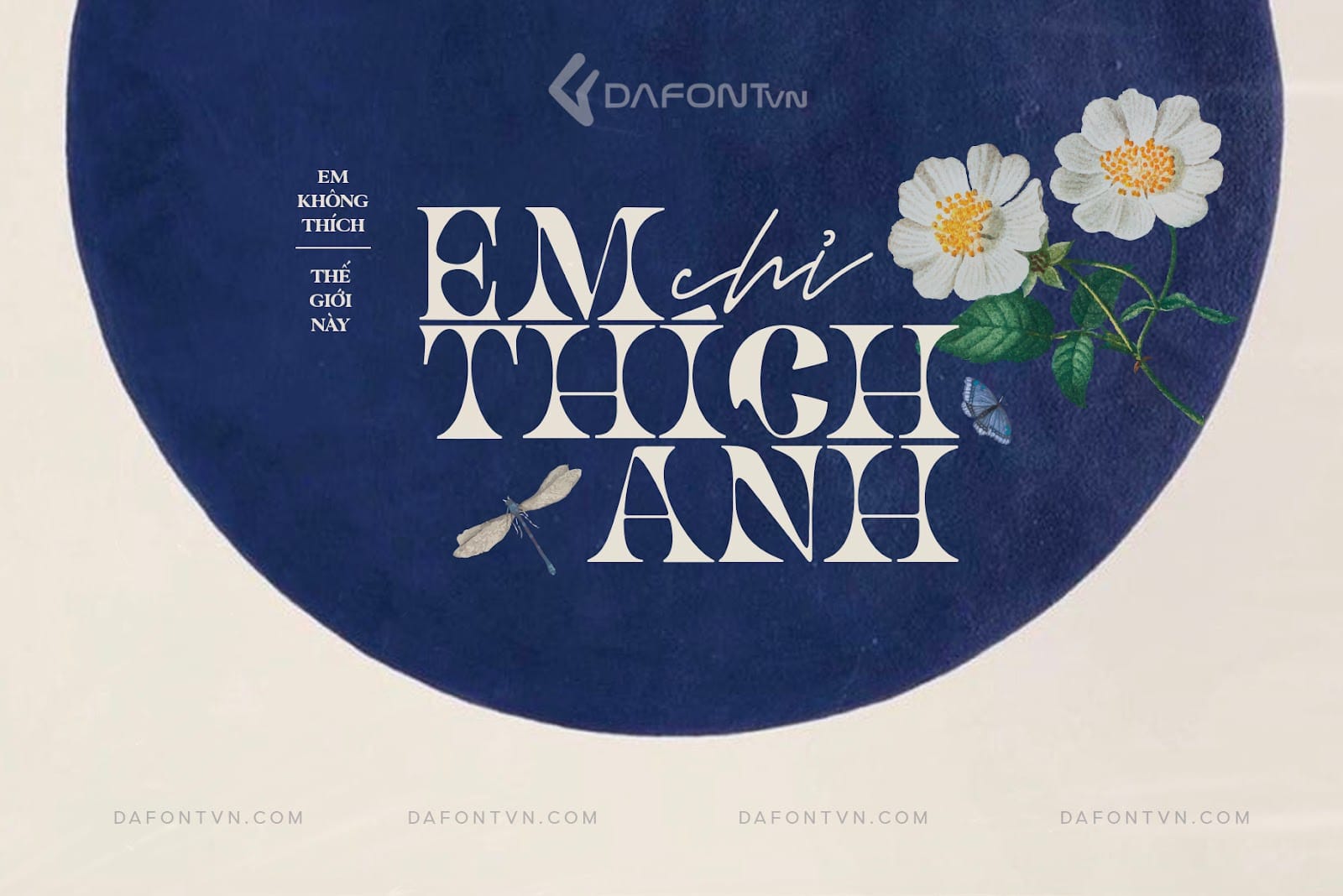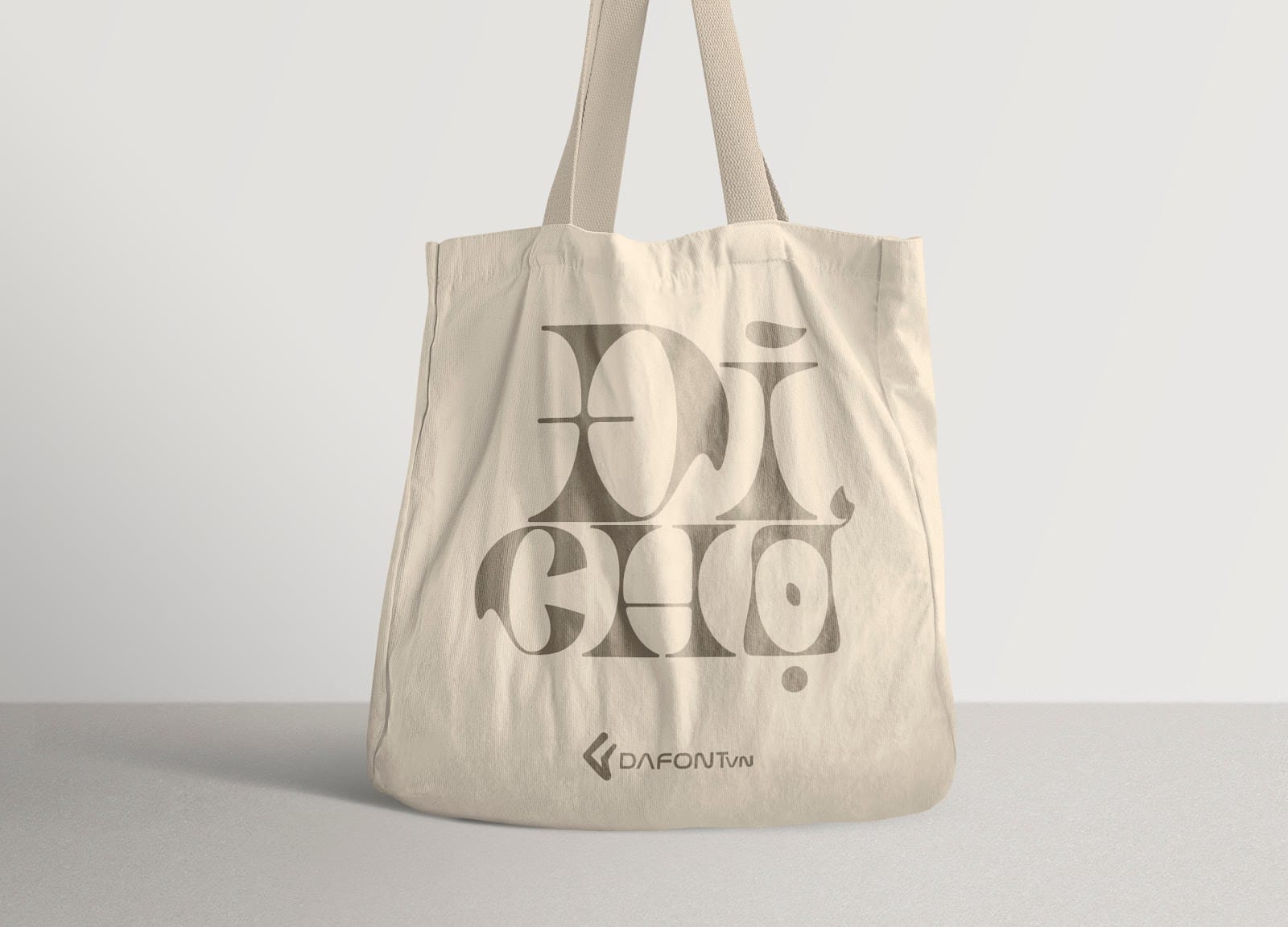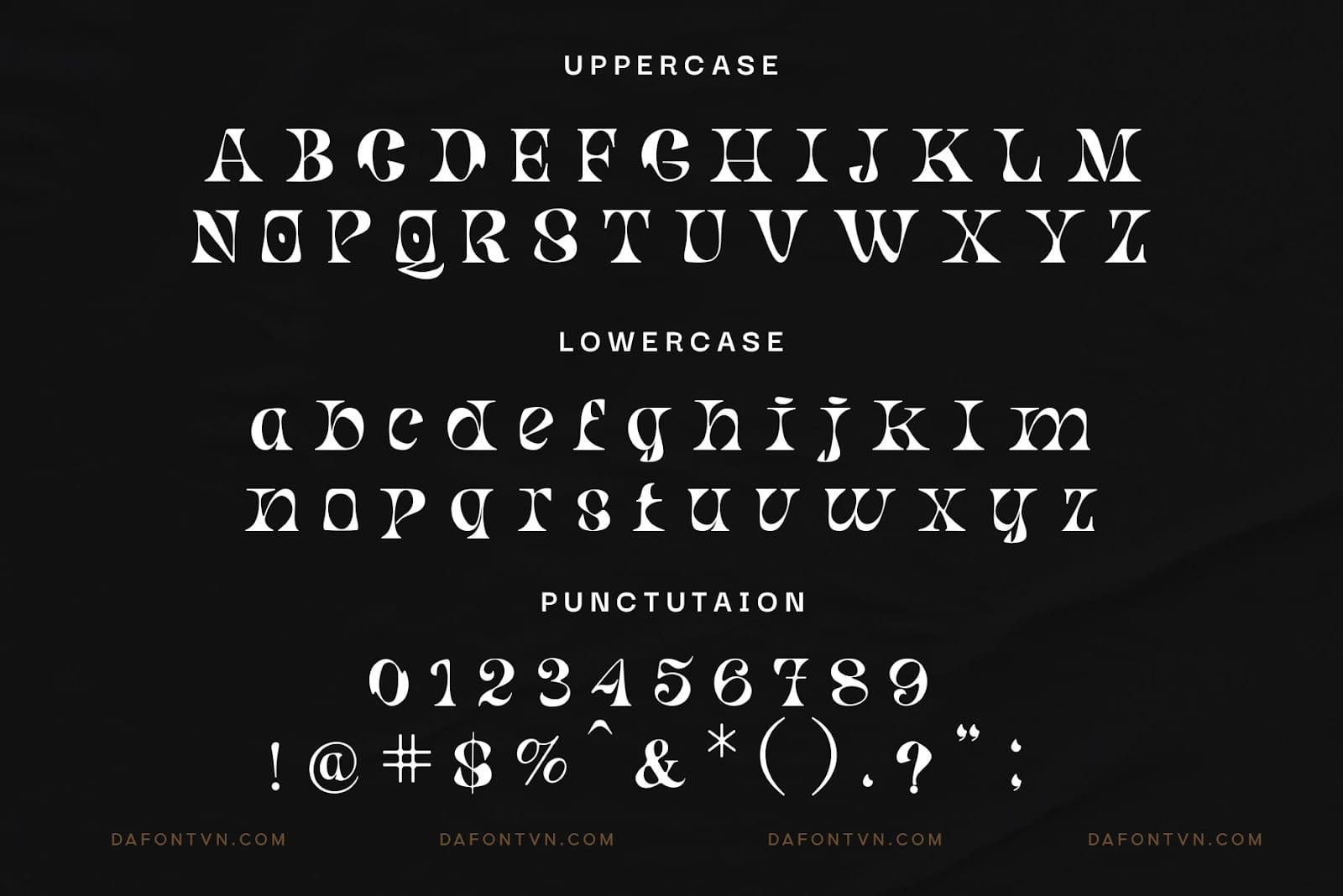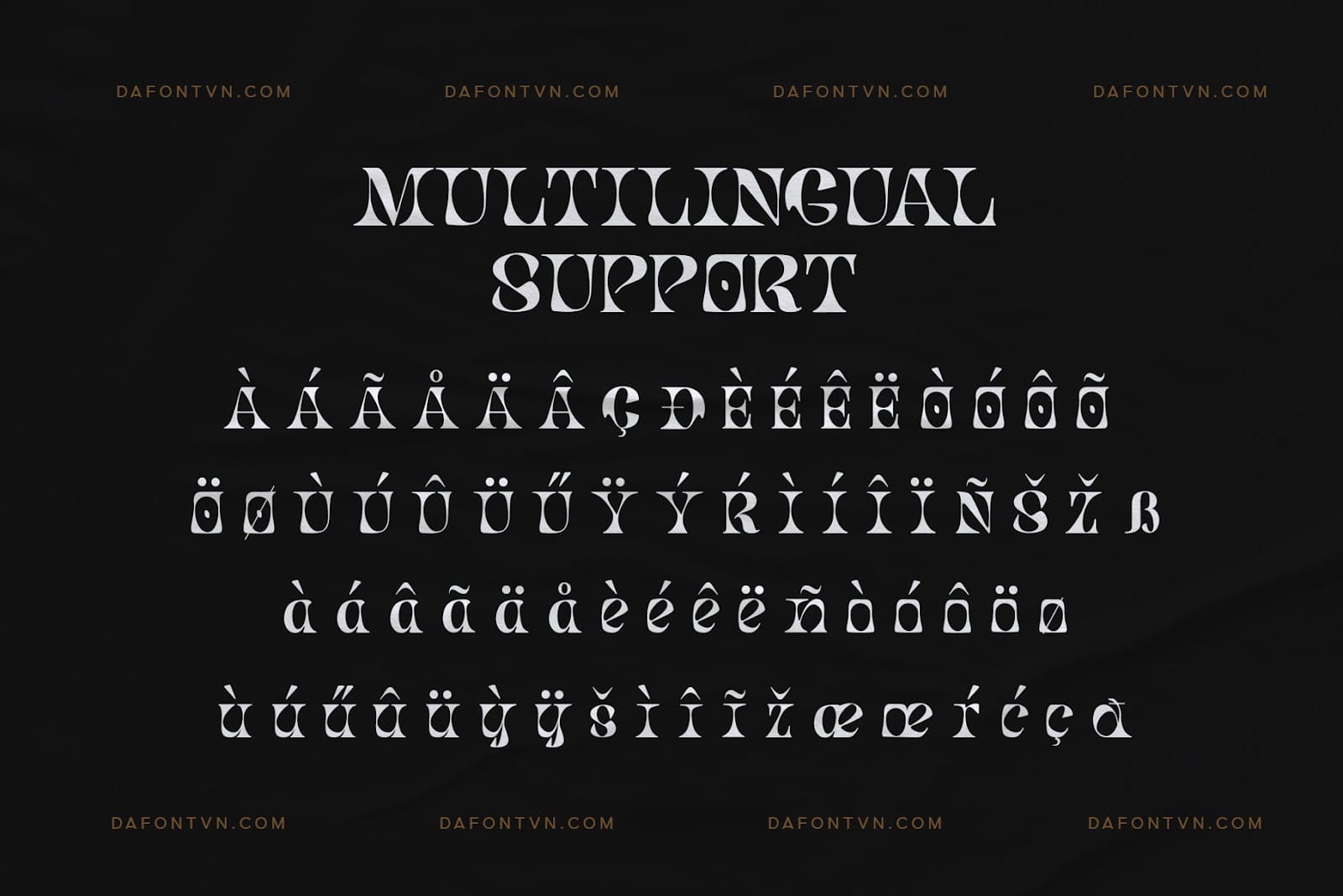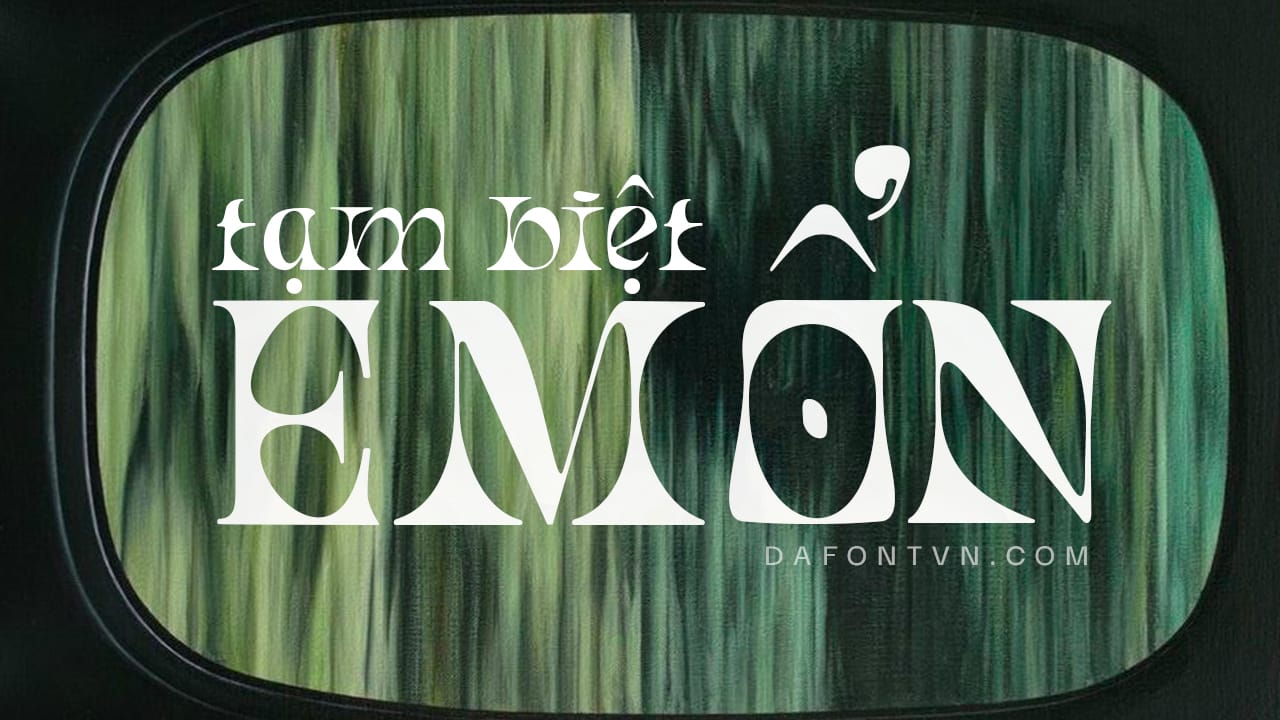
Armies Display Font là một kiểu chữ “twisted shape” (xoắn quẩy) với các nét được thiết kế khá độc đáo. Mặc dù nó dễ đọc ở kích thước trung bình nhưng nó sẽ đẹp hơn khi được sử dụng ở kích thước lớn nơi bạn muốn làm nổi bật chi tiết cho các thiết kế của mình. Bạn có thể sử dụng nó ở các chữ hoa và chữ thường.
Nó có thể sử dụng hoàn hảo cho các dự án sáng tạo logo, tạp chí, thư mời, bao bì, tiêu đề, áp phích, thiệp mời, áo phông / trang phục… hoặc bất kỳ thiết kế nào khác cần một font chữ hiển thị ấn tượng, độc đáo hoặc một chút táo bạo trong thiết kế của bạn.
Font Armies Display việt hóa đầy đủ, kerning, chỉnh sửa lại 1 số dấu và tối ưu hóa để có thể sử dụng trên bất kỳ phần mềm nào.